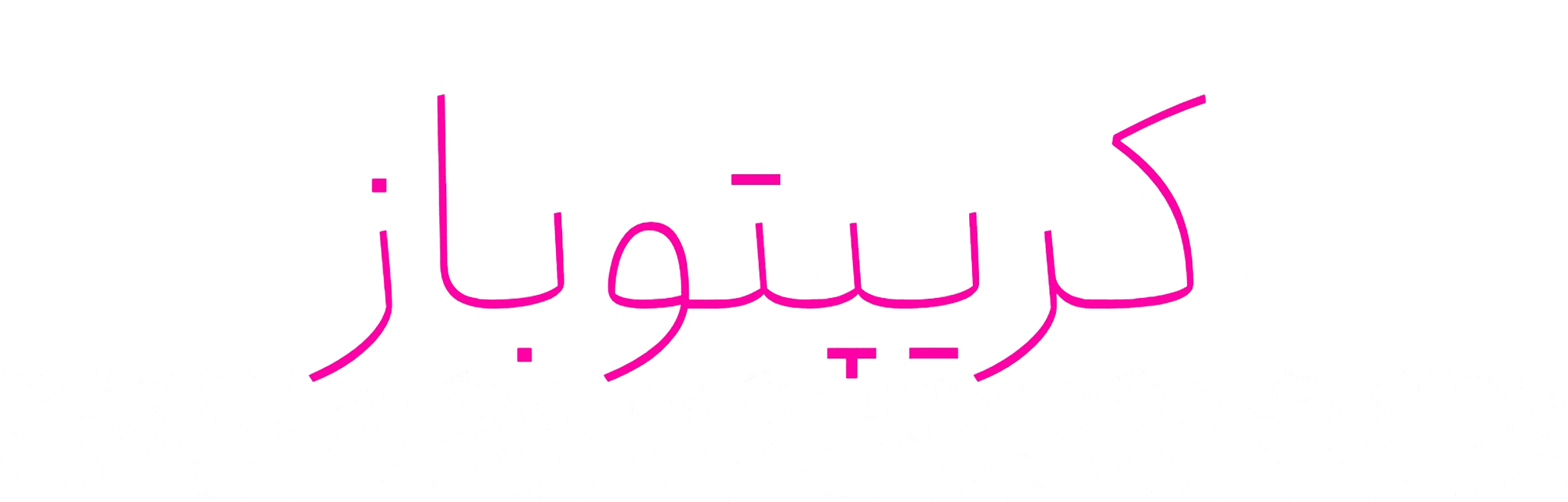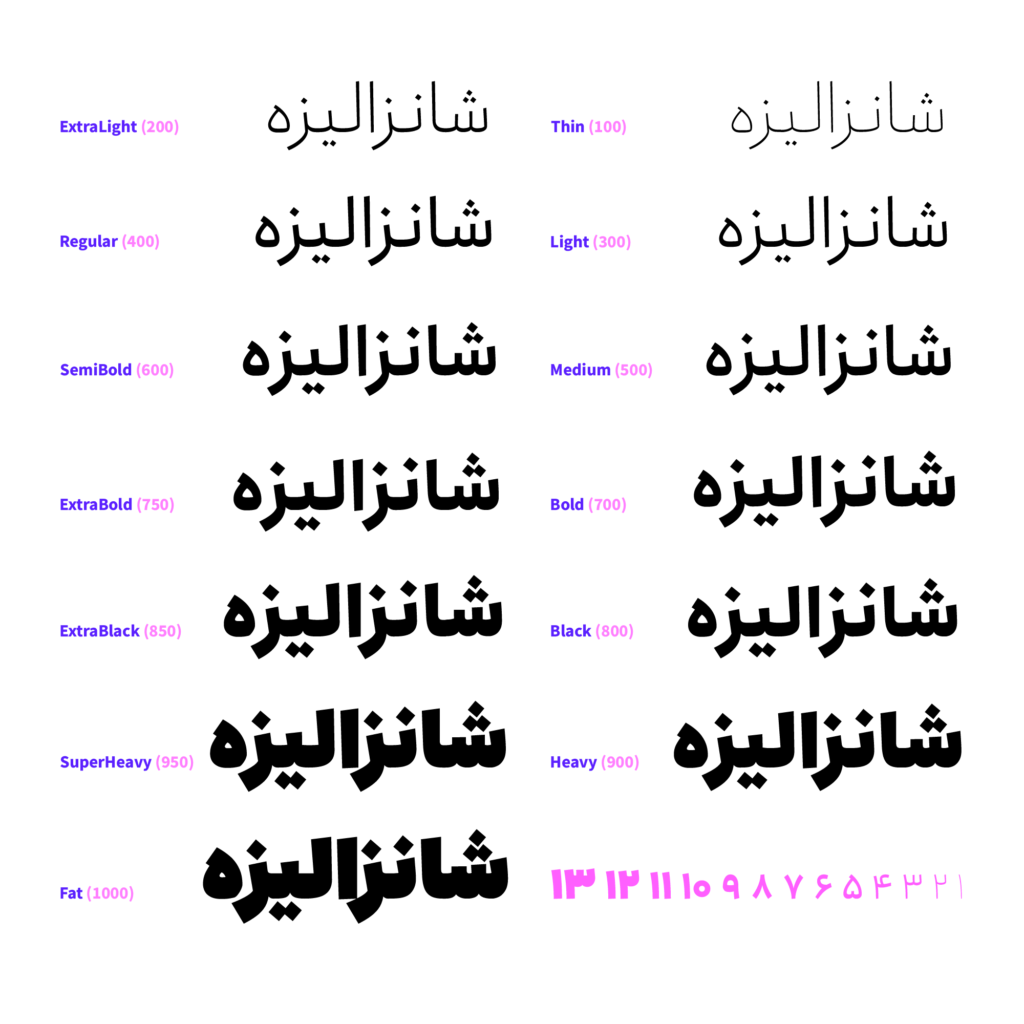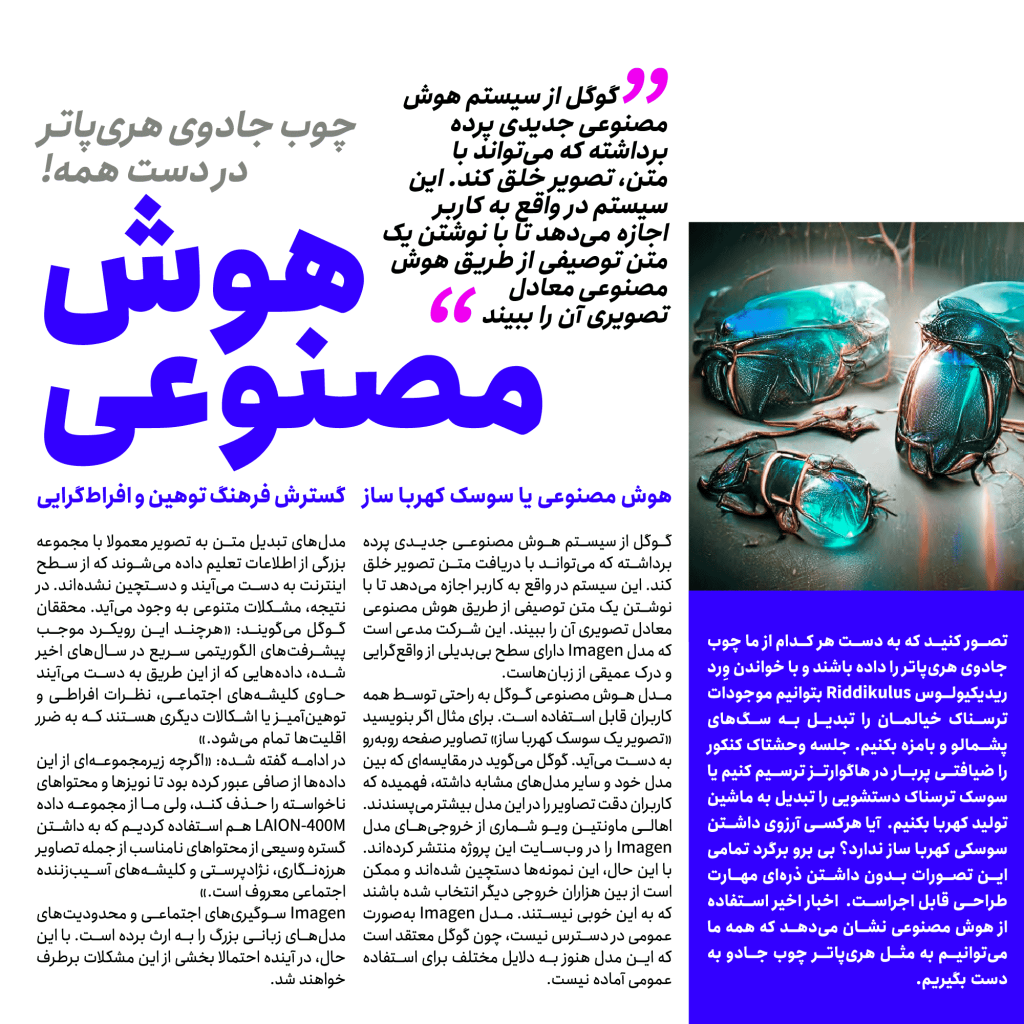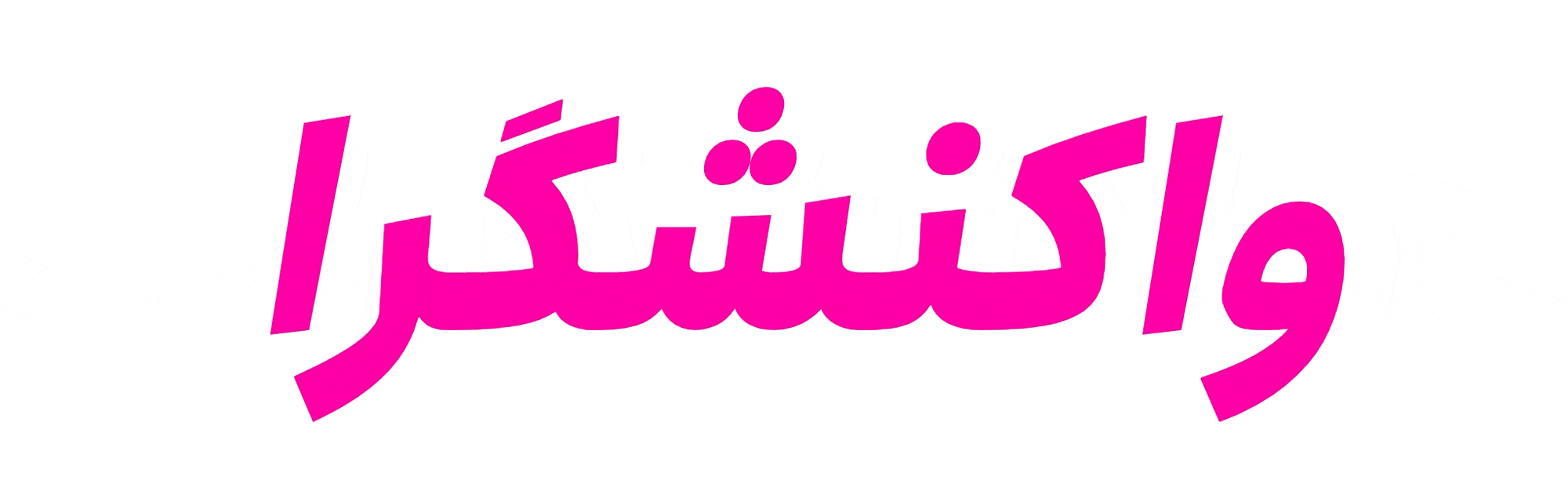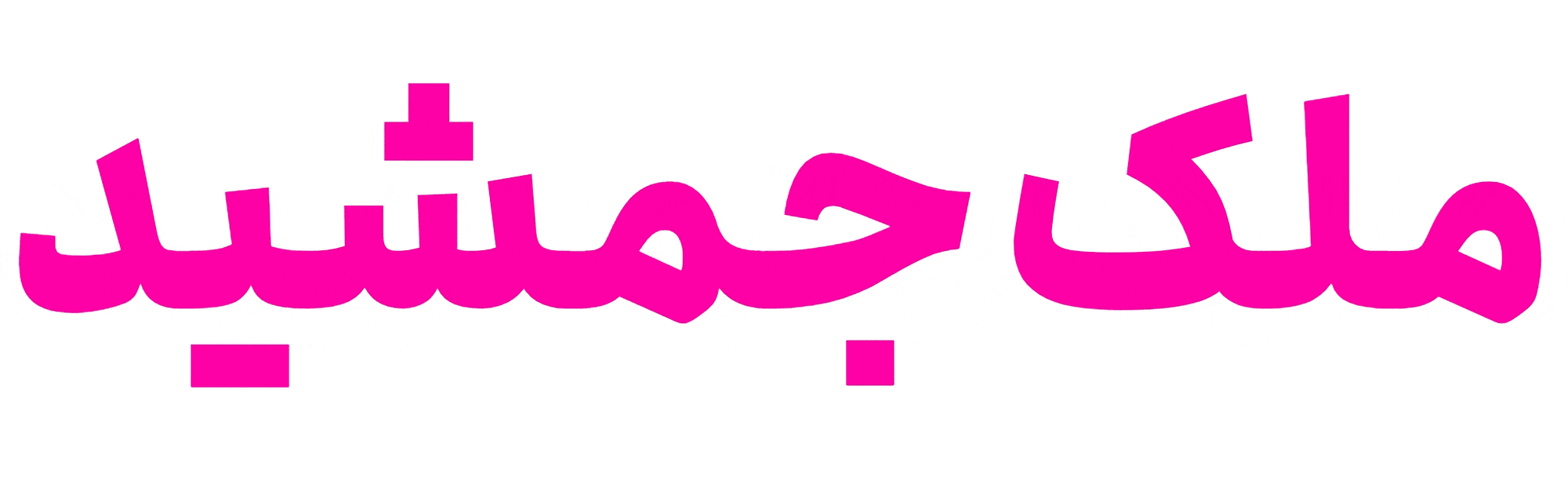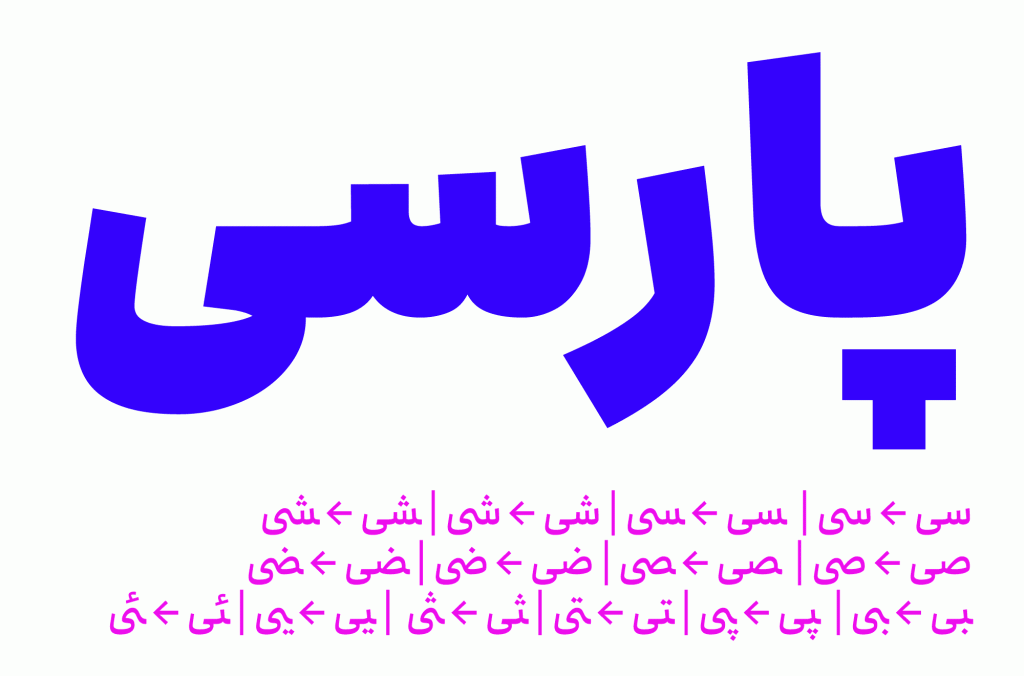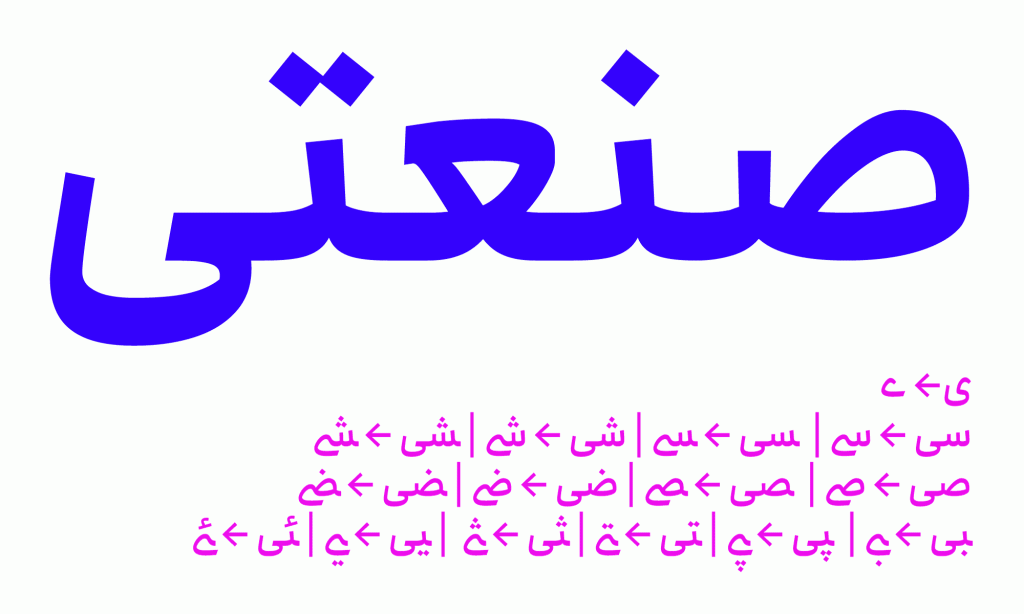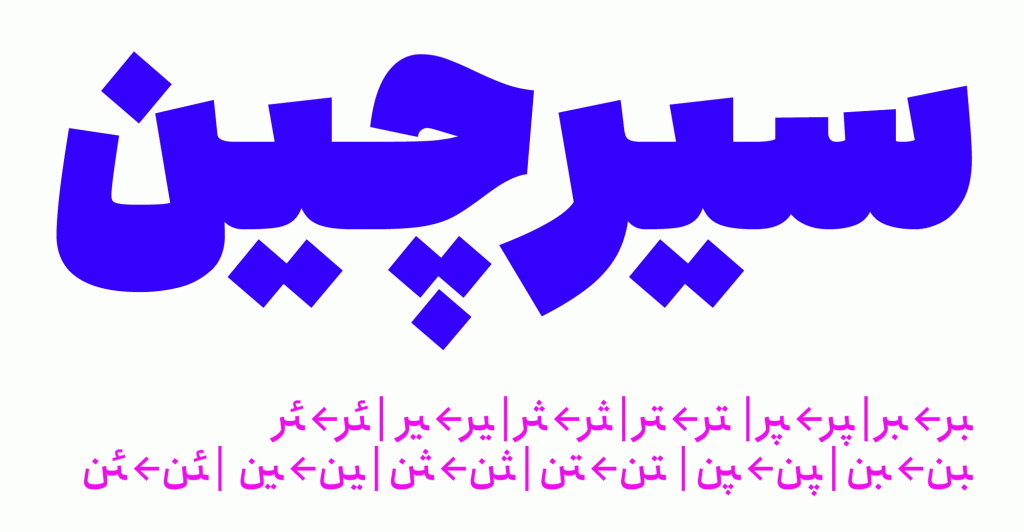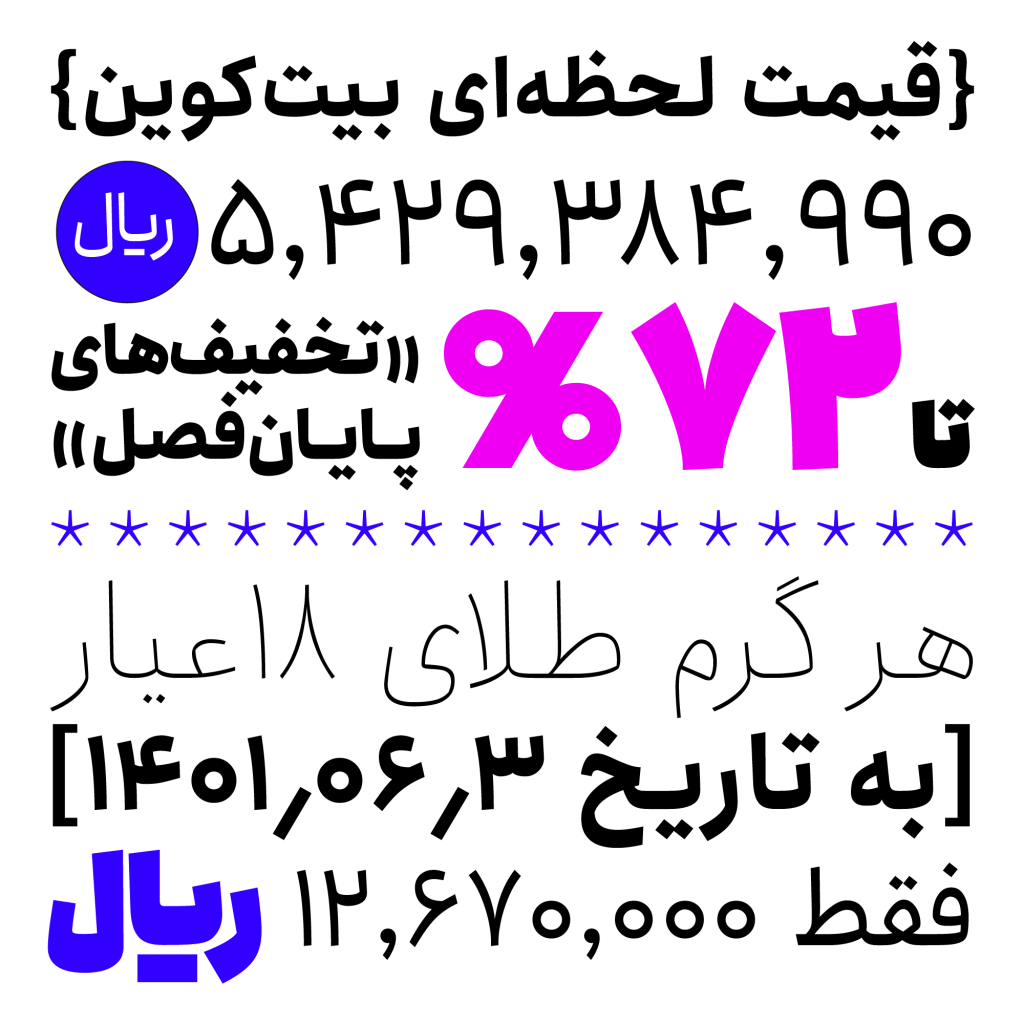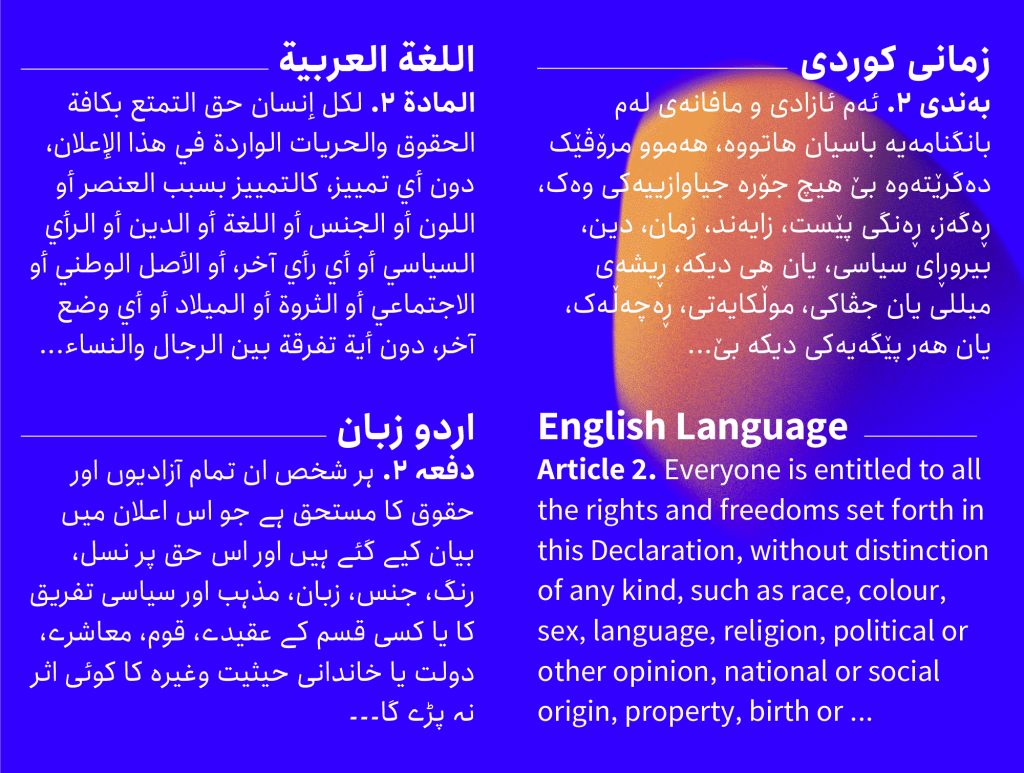
فونت انجمن قلمی که به علت خوانایی فوق العاده و زیبایی هرچه بیشتر آن موفق به دریافت جایزه اول دوسالانه سرو نقره ای در سال 98 گردیده است . با ما همراه و در ادامه تصاویر زیبای این تایپ فیس را مشاهده فرمائید.
فونت انجمن – قلمی با خوانایی شگفت انگیز
فونت انجمن قلمی بسیار زیبا که با کوشش و تلاش هیربد لطفیان پا به عرصه تایپوگرافی گذاشته است. اگر به دنبال فونتی با خوانایی بالا برای متون طولانی در مطبوعات، رابط های کاربری ، صفحات وب ، چاپ و … برای خود می باشید انجمن بهترین انتخاب می باشد . حتی همین لحظه که مشغول خواندن این متن در سایت ما هستید مطمئنا با خوانایی بالای این تایپ فیس آشنا شده اید.
یکی از دلایل این خوانایی بالا در انجمن را می توان سادگی سبک طراحی و تعیین دقیق فاصله‌گذاری و تنظیم فضاهای مثبت و منفی دانست که خروجی این اقدامات در طراحی شکل گیری تایپ فیسی با این درجه از خوانایی و زیبایی گشته است.
انجمن نه تنها انتخابی مطمئن برای متن های طولانی بلکه در بحث عناوین و تبلیغات نیز حرف ها برای گفتن دارد . در واقع با این قلم تمامی نیاز های شما مرتفع خواهد شد . شیوه طراحی همانند فونت نورا را معادلی نسبی برای حروف انگلیسی سن‌سریف دانست.
به عبارت ساده تر انجمن را می توان یکی از جامع‌ترین فونت‌هایی است که طراحان و کاربران می‌توانند در سبد دیزاین خود داشته باشند و در واقع آچار فرانسه آنها به شمار می رود که گستره‌ و طیف وسیعی از وزن‌ها را برای دست طراحان در استفاده نمایشی و سایز کوچک باز می‌گذارد.د .
انجمن مَکس دارای ۱۳ وزن است که تمامی این وزن‌ها در سبک‌های ایتالیک (Italic) و فشرده (Condense) نیز طراحی شده‌اند. انجمن یکی از جامع‌ترین فونت‌هایی است که طراحان و کاربران می‌توانند در سبد دیزاین خود داشته باشند. گستره‌ وسیع وزن‌ها دست طراحان را برای استفاده نمایشی و سایز کوچک از فونت باز می‌گذارد.
انجمن مَکس تایپ‌فیسی مدرن و جدید می باشد که با دارا بودن فرم‌هایی ساده و ارگانیک، حالتی دلنشین و گیرا از واژگان و حروف را می‌سازد. نسخه جدید (مکس) منعطف و معتدل و نرم است؛ به عبارتی می توان گفت جایی میان سادگی و پیچیدگی ایستاده است حالتی از اعتدال. به همین سبب از استقبال بالایی از کاربران، مخاطبان و خوانندگان برخوردار گشته است و محبوبیت بی نظیر در همگان برای خود رقم زده است.
همانطور که پیش تر نیز گفته شد خانواده فونت انجمن تکمیل کننده نیاز طراحان تایپوگرافی است و کمبودی در آن وجود ندارد این قلم زیبا با دارا بودن طیف گسترده و تنوع بالا در وزن های مختلف (13 وزن مختلف) حداقل آن ۱۰۰ معادل وزن Thin و حداکثر آن ۱۰۰۰ معادل وزن Fat می‌توان نمایش دلخواه را با حروف کارگردانی نمود.
نسخه وریبل فونت انجمن و حالت های نقطه گذاری آن مختلف
در پکیج مکس این قلم نسخه متغییر و وریبل وجود دارد . نسخه ای که فواید بالای آن از جمله حجم کم وسرعت بالای لود صفحات است. همچنین نقطه گذاری های مختلف نیز در این فایل وجود دارد.
پشتیبانی از حروف جایگزین
در فونت انجمن می توانید با فعال کردن استایل ها در قسمت Opentype Features از فرم‌های جایگزین‌ حروف بهره مند گردید . از جمله این حروف می توان به ” ی – ر – ز -ژ – ک – گ – و …. ” اشاره نمود. همه می دانیم که این قابلیت علاوه بر ایجاد توع و افزایش زیبایی بر آزادی عمل شما در خلق آثار زیبا می افزاید.
متمایل به راست در نسخه مکس
می‌توانید در انجمن مکس حالت ایتالیک ((یعنی به سمت راست مایل می‌کند) را جهت زیبایی هرچه بیشتر نیز به کار برید و با الگو برداری نوشتار فارسی، خط شکسته نستعلیق را پیاده سازی نمائید. حروف ایتالیک در فونت انجمن مکس بر پایه‌ همین منطق به سمت راست مایل ‌است. مایل بودن به سمت راست علاوه بر پیشینه‌ای که در حروف فارسی دارد، با حروف ایتالیک لاتین نیز هماهنگ‌تر می باشد.
مقدار این اندازه از تمایل به سمت راست را متغیر Slant می نامیم این متغییر نوشته‌ها را تا 8 درجه ایتالیک می‌کند . پس حداقل آن صفر و حداکثر آن 8 است.
فشردگی در نسخه مکس
یکی از بزرگ‌ترین چالش‌های دیزاینر‌ها فشرده کردن حروف در تایپوگرافی است. انجمن مکس با پشتیبانی قابلیت  (Condensed)  یا سبک فشرده راه‌حل حرفه‌ای و سالم ارائه نموده است؛ که با جابه‌جایی یک بازو (وریبل)، به راحتی آبخوردن در دسترس است.
متغیر Width در وریبل فونت انجمن مکس : این متغییر می‌تواند ۲۰ درصد حروف را فشرده (Condensed) کند حداقل این متغییر ۸۰ و حداکثر آن ۱۰۰ است.